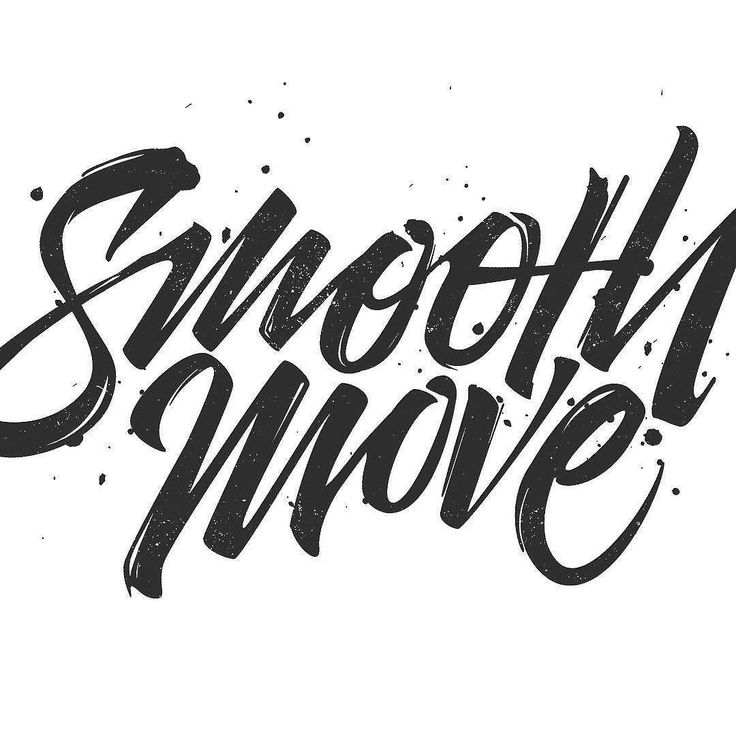
5 инсайтов психологии шрифта, которые улучшат ваш UX
Психология шрифтов — это еще одна наука дизайна, которую вы должны тщательно изучить, чтобы стать хорошо образованным дизайнером с широким кругозором.
Каждый шрифт имеет свою индивидуальность, поэтому вам стоит познакомиться с ним поближе. Каждый шрифт влияет на то, как мы воспринимаем бренд и продукт, поэтому вы должны знать эти скрытые влияния на процесс принятия решений пользователем. Каждый шрифт влияет на эмоции, которые мы ассоциируем с продуктом, и создает определенную эмоциональную связь с брендом. Таким образом, вы должны быть в состоянии идентифицировать «личность» шрифта и сопоставить ее с личностью бренда.
В этой статье мы рассмотрим различные этапы познания шрифта и поможем вам определить, как различные шрифты влияют на нашу психику.
Психология шрифта с засечками
Шрифт с засечками так же традиционен, как и Бурбон. Он вполне себе предсказуемый, элегантный и рациональный.
Этот шрифт имеет особенность, о которой должен знать каждый дизайнер — шрифты с засечками менее читаемы на экранах.
Light и Bold шрифты
Тонкие шрифты чаще всего ассоциируются с утонченностью, женственностью и красотой. На примере косметических брендов можно убедиться в этой теории (Avon, MAC, Becca и т.д.). Мы хотим показать разработанный нами логотип для магазина ювелирных изделий.
Это может показаться почти незаметным, но на самом деле даже малейшие намеки в шрифте логотипа могут вызвать разное отношение клиента к бренду и ассоциации.
Скругленные VS рубленные
Известный факт, что люди предпочитают изогнутые или округлые формы, а не острые. Почему? Это вызвано унаследованными инстинктами самозащиты. Постарайтесь выяснить свое первое чувство, вызванное именно в тот момент, когда вы увидели большой и острый нож. Правильно… Это ощущение угрозы. То же самое мы подсознательно испытываем при взаимодействии с резкими формами и угловатыми шрифтами в дизайне. Они могут вызвать чувство опасности, мужественности и долговечности, что может быть полезно для дизайнера, который хочет добавить щепотку адреналина и опасности в дизайн.
Однако будьте осторожны при использовании «опасных» шрифтов. Применяйте их в нужном месте. Представьте себе, «опасный» дизайн логотипа для бренда детского питания. Нет, здесь это не сработает. Вы должны соответствовать индивидуальности бренда и чертам, передаваемым шрифтом.
Вы можете использовать округлые шрифты для бренда, связанного с понятиями мягкости, комфорта, женственности, красоты или даже сладкой пищи.
ЗАГЛАВНЫЕ VS строчные буквы
Строчные буквы обычно ассоциируются с понятиями сострадания или новаторства. Поэтому строчные буквы могут быть эффективно использованы в дизайне, созданном для компаний — «опекунов» или для брендов — «создателей продуктов».
Заглавные буквы чаще всего ассоциируются с понятием власти. Всемирно известные коммерческие гиганты, такие как BMW, Nike и Sony, имеют заглавные буквы в своих логотипах, чтобы подчеркнуть силу своего социального влияния, энергию и успех.
Строчные и прописные буквы могут быть легко объединены в один текст, что делает его более читабельным для пользователей. Когда вы смешиваете их с шрифтами, вы непреднамеренно создаете так называемый эффект конгруэнтности ожиданий. Это означает, что люди легче воспринимают текстовый формат, если он соответствует их ожиданиям.
Буквы смешанного регистра имеют разную высоту, что позволяет пользователям воспринимать больше различий между буквами.
Узкие VS широкие
Узкие и широкие шрифты — это две крайности дизайна. Обычно мы воспринимаем узкие шрифты как нечто, связанное с понятием герметичности. Этот шрифт создает ощущение ограниченного пространства, напряжения и точности. Его можно воспринимать как нечто ограничивающее в движении. Однако, играя в игру с чувствами и эмоциями пользователя, вызванными строгой сжатой индивидуальностью шрифта, вы можете добавить определенную нотку экстравагантности и смелости в свой дизайн.
И напротив, расширенные шрифты передают понятия простора и расслабления. Широкие шрифты делают дизайн дышащим и легким. Они обычно применяются в дизайне брендов, которые стремятся выглядеть позитивно и легко для своей целевой аудитории.
Короткие VS высокие
Короткие шрифты обычно передают ощущение тяжести и стабильности, в то время как высокие шрифты передают идею легкости и роскоши.
Мы подсознательно связываем высоту шрифта с метафорическими понятиями гравитации. Например, горизонтальная ориентация, подчеркнутая в коротких шрифтах, предполагает тяжесть и солидность. Он воплощает в себе понятия долговечности, устойчивости и чего-то неподвижного.
Высокие шрифты изображают легкость и быстроту. Он также может быть метафорически связан с устремлением и честолюбием. С другой стороны, многие люди связывают вертикальность, подчеркнутую высокими шрифтами, с концепцией роста, успеха и роскоши. Именно поэтому многие дизайнеры часто используют высокие шрифты в дизайне люксовых брендов.
Найдите ваш шрифт!
Психология шрифтов — это очень логичная и интуитивная наука, которая может быть прекрасно применена в процессе творческого проектирования. Каждый шрифт имеет свою индивидуальность, свои скрытые черты и влияет на психику пользователя. Главная задача дизайнера — раскрыть эту индивидуальность и соотнести ее с настроением бренда.